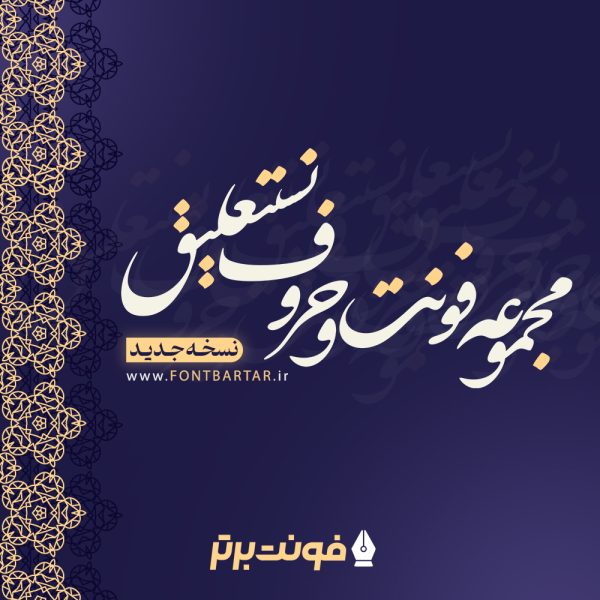
مجموعه فونت و حروف نستعلیق
شما هم تا به حال تایپوگرافی های زیبا با خط نستعلیق را در فضای مجازی و نمونه کار طراحان گرافیک مشاهده کرده اید، شاید در ذهن شما هم این سئوال شکل گرفته باشد که من فونت نستعلیق رو دارم اما هیچ کدام از حروف شبیه حروف طراحی شده نیستند! جواب تمام سئوالات اینجاست…
مجموعه فونت و حروف نستعلیق فارسی
فونت نستعلیق فارسی یکی از زیباترین و اصیلترین فونتهای خوشنویسی ایرانی است که در طراحی گرافیکی، تایپ فارسی، پوسترسازی، دیزاین وب و تولید محتوا کاربرد گستردهای دارد. در این صفحه، مجموعهای کامل از فونتهای نستعلیق حرفهای و حروف نستعلیق فارسی را برای شما آماده کردهایم تا بتوانید با کیفیت بالا در پروژههای گرافیکی خود استفاده کنید.
مجموعه فایل طراحی شده و آماده حروف، نقطه، اعراب نستعلیق ( بدون پس زمینه ) به همراه مجموعه کامل 38 فونت نستعلیق را در یک پکیج آماده کردیم که می توانید از آن در انواع محیط های طراحی گرافیک مثل موبایل / کامیپوتر در نرم افزار های مختلف استفاده کنید.
این پکیج شامل چه حروفی می باشد؟
- آ ا – ب پ ت ث – ج چ خ ح – د ذ ر ز ژ – س ش ص ض – ط ظ – ع غ – ف ق – ک گ – ل – م – ن – و – ه – ی
- نقطه ها و اعراب
- حروف چسبیده و متصل
ویژگی های مجموعه حروف کشیده نستعلیق:
- کیفیت بالای حروف بدون افت کیفیت
- مجموعه انواع حروف به شکل های مختلف
- مجموعه بیش از 400 حروف
پکیج فونت و حروف نستعلیق شامل:
- سری اول حروف
- سری دوم حروف
- اعراب
- اضافه شدن حروف جدید جدید
- اضافه شدن حروف متصل جدید
- اضافه شدن فونت های اختصاصی نستعلیق جدید
فونت نستعلیق فارسی یکی از ارزشمندترین میراثهای خوشنویسی ایرانی است که امروزه در قالب فونتهای دیجیتال در اختیار طراحان و هنرمندان قرار گرفته است. با دانلود این مجموعه کامل فونت و حروف نستعلیق فارسی میتوانید اصالت، زیبایی و هنر ایرانی را در طراحیهای خود زنده نگه دارید.